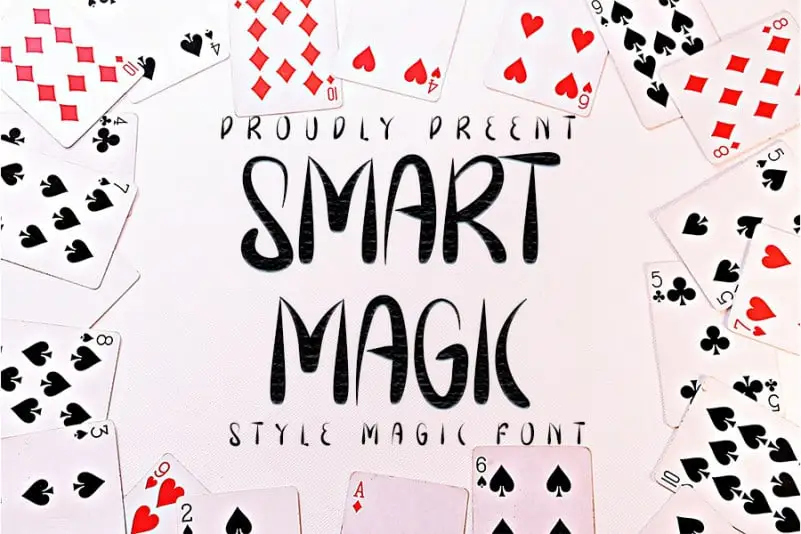
Smart Magic Display Font é uma elegante fonte escrita a mão que mantém influências do calligrafico clássico ao mesmo tempo que parece atual e jovial, oferecendo versatilidade perfeita para diversas ideias criativas. A sua fluidez e personalidade fazem dela um recurso ideal tanto para criações de cartões, como títulos, quanto para estilos de papelaria. Como uma fonte display, ela se destaca em textos mais expressivos e poderosos, tornando-a perfeita para criar impacto nas aplicações digitais ou impressas. Esta fonte é ideal tanto para designers experientes quanto para aqueles que desejam adicionar um toque único a seus projetos de design gráfico.